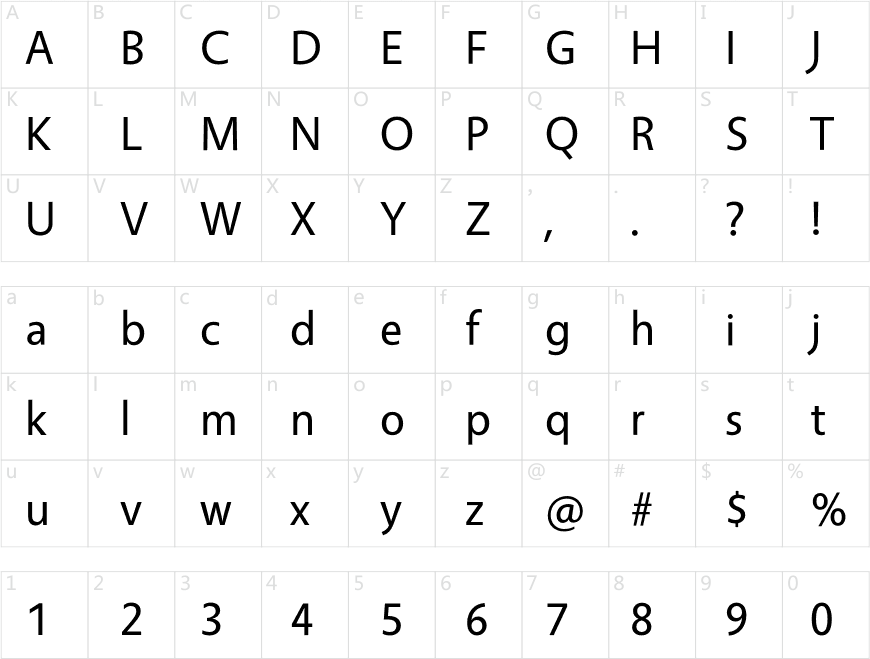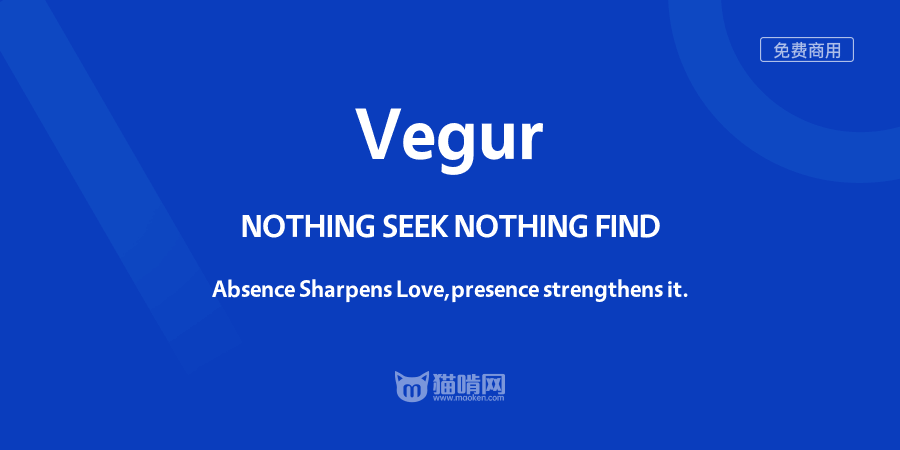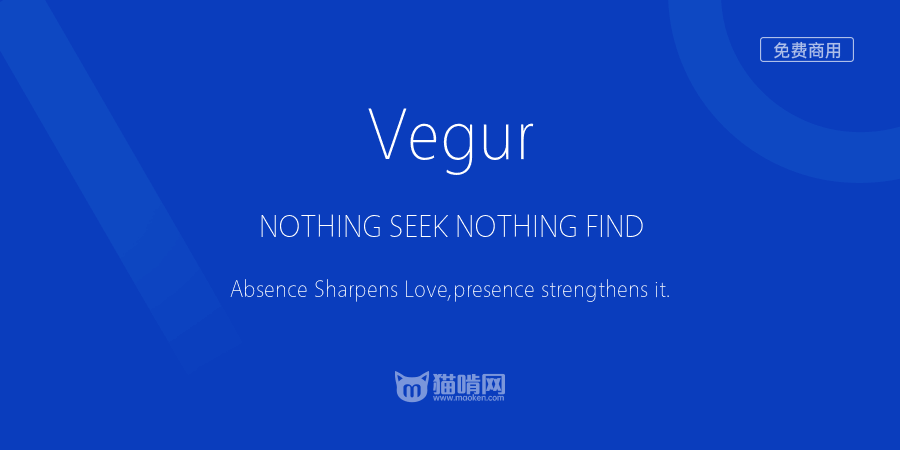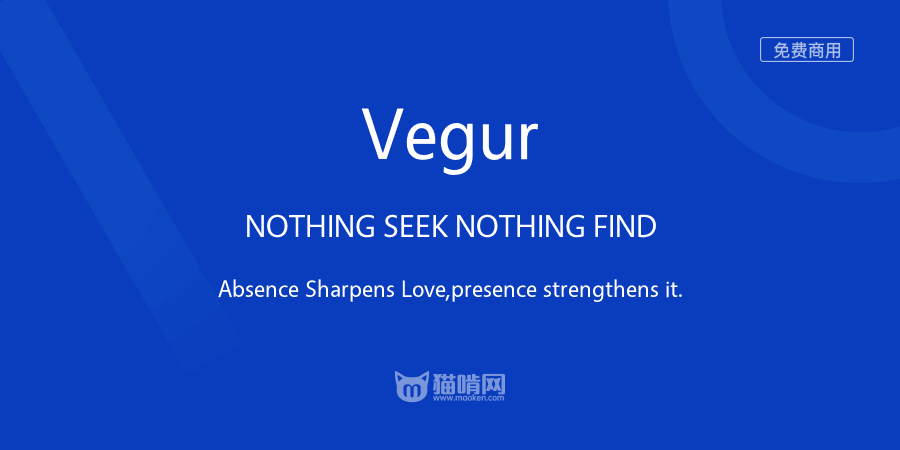
Vegur
字体作者:佐賀野 宇宙 (日本) 字体字重:3个
Vegur是为dot colon的logo类型开发的字体。
以0.700版本的更新为契机,重新审视了设计,整理了拖延的部分,给人留下了尖锐的印象。另外,比以前的版本调整为长体,整体给人一种清爽的印象。特别是拖延的Bold权重在这次的更新中给人留下了很大的印象。
除此之外,还有对话记号(字母表上的记号)和法语的符号Œ中描述的场景,使用以下步骤创建明细表,以便在概念设计中分析体量的体积。此外,还追加了英镑€(欧元)等代表性货币符号和欧洲圈的约物符号。虽然还不是所有的文字、记号都齐全,但是打算在今后的更新中依次追加。
作为发展型,公开了大幅增加设计刷新和收录网格数的Route159。